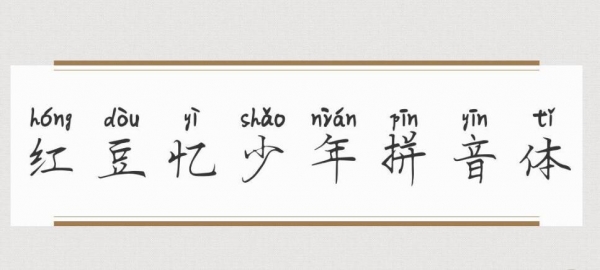
紅豆憶少年拼音體是一款非常不錯(cuò)的手寫(xiě)拼音字體,個(gè)性醒目,具有強(qiáng)烈的視覺(jué)沖擊力,適應(yīng)于報(bào)紙和雜志和書(shū)籍中常用字體, 海報(bào)、個(gè)性促進(jìn)品牌標(biāo)志設(shè)計(jì)、字體設(shè)計(jì)、等環(huán)境使用,歡迎喜歡的朋友前來(lái)下載使用。